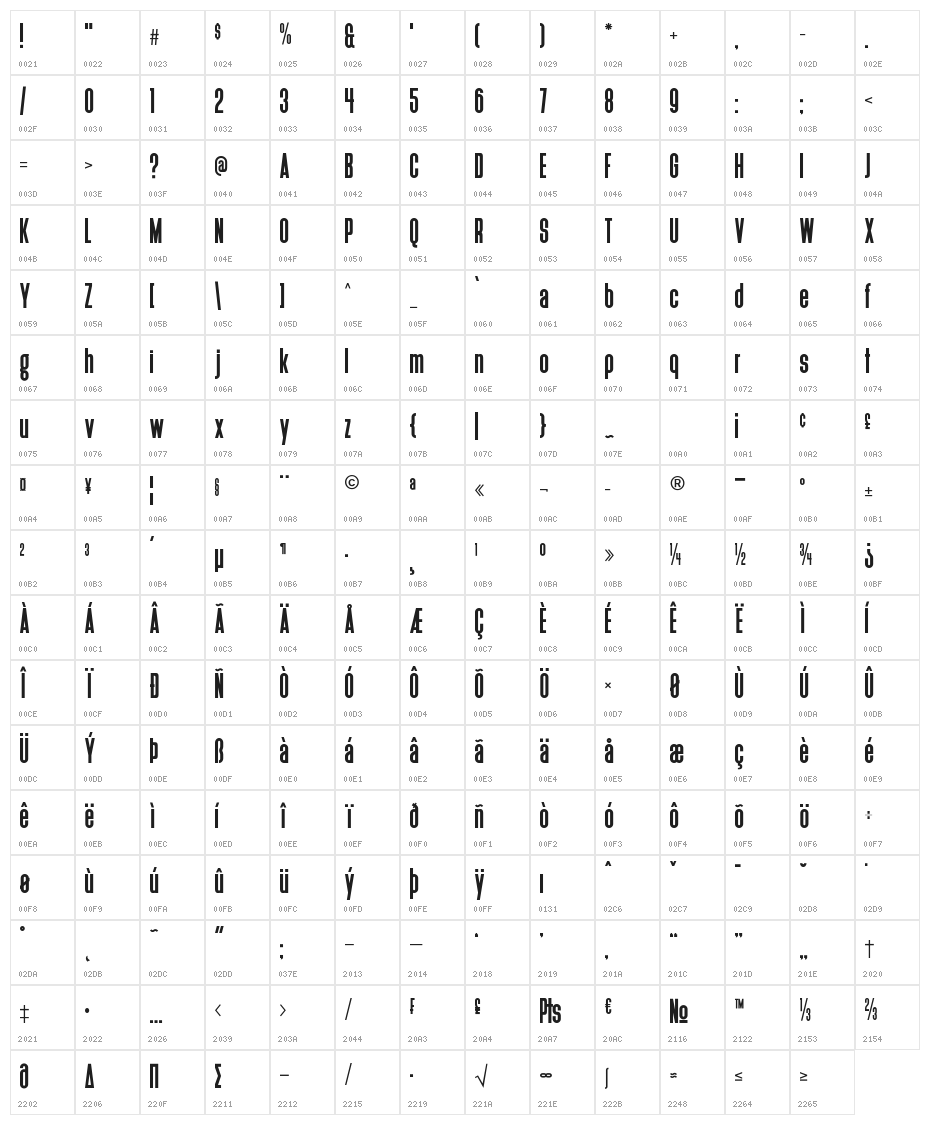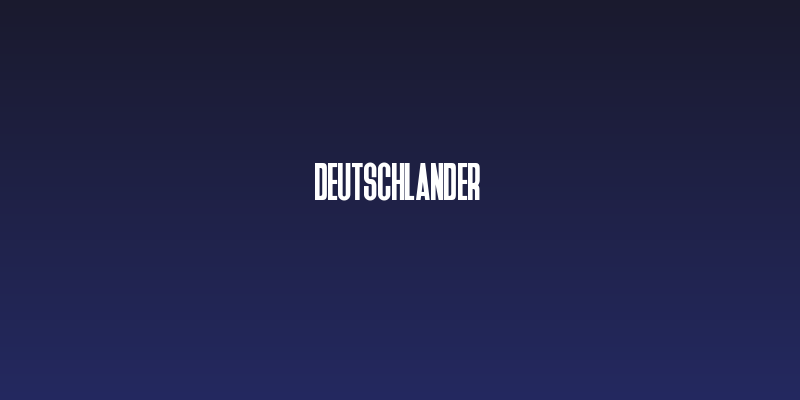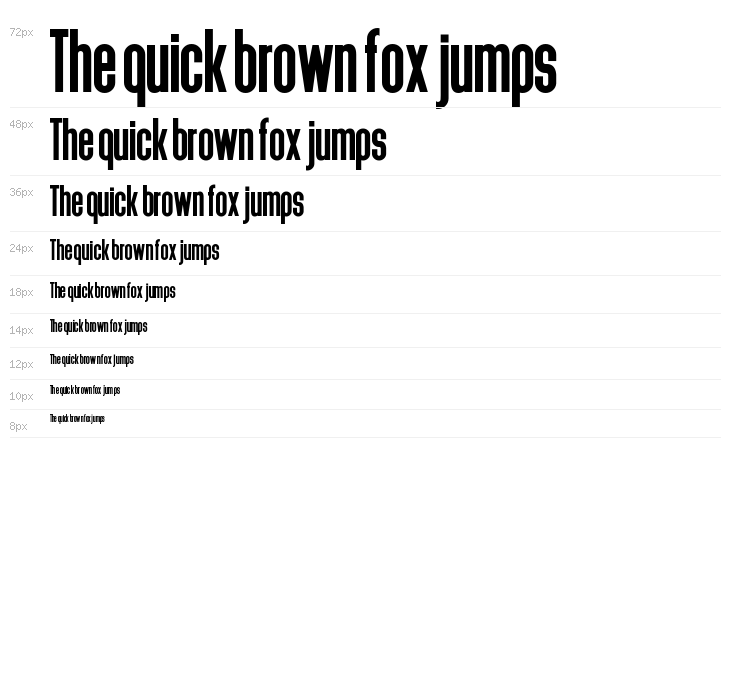
Deutschlander Font
| Gesamtstil | Vintage, Modern |
| Vorgeschlagene Projekte | This font is perfect for poster designs, headlines, branding projects, and any application where a strong visual impact is desired. |